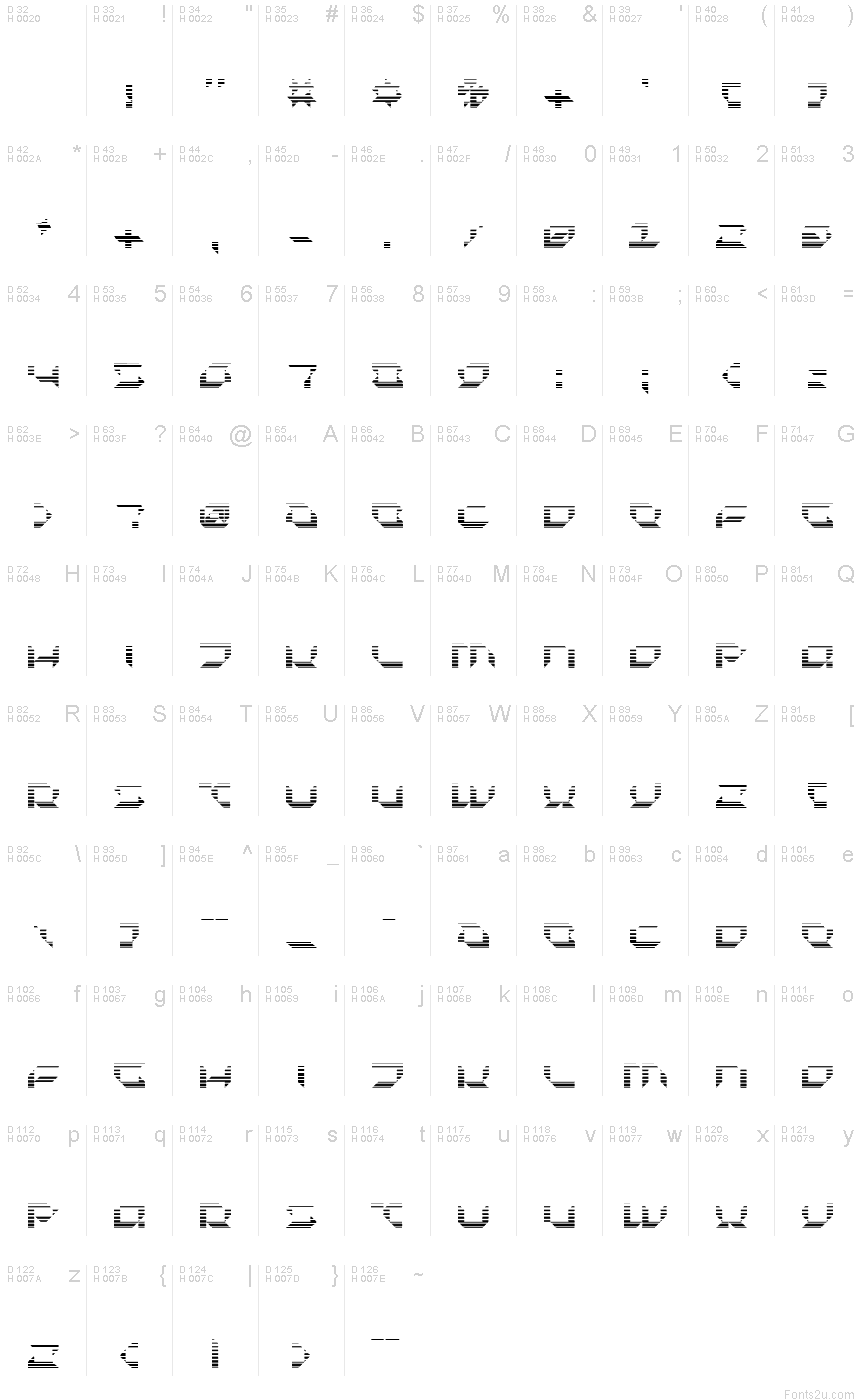
Pluranon Fade autorstwa Milana Zrnica i Tommy’ego Cary’ego to darmowy font techno typu display o surowym, przypominającym sygnał rytmie. Litery zbudowane są ze stosów poziomych pasów i ostrych cięć, dzięki czemu alfabet wygląda jak połączenie grafiki obwodów drukowanych i dynamicznego liternictwa w stylu cyfrowej kultury wczesnych lat 2000.
Idealnie pasuje do plakatów, tytułów gier, ulotek klubowych, opakowań sci-fi i brandingu opartego na interfejsach, wszędzie tam, gdzie potrzebujesz darmowego fontu z mocniejszym, elektronicznym pulsem niż w przypadku neutralnych krojów displayowych. Ponieważ formy rozbijają się na powtarzalne paski, krój świetnie sprawdza się również w krótkich nagłówkach, planszach tytułowych i monogramach, gdzie to właśnie puste przestrzenie wykonują całą pracę wizualną.